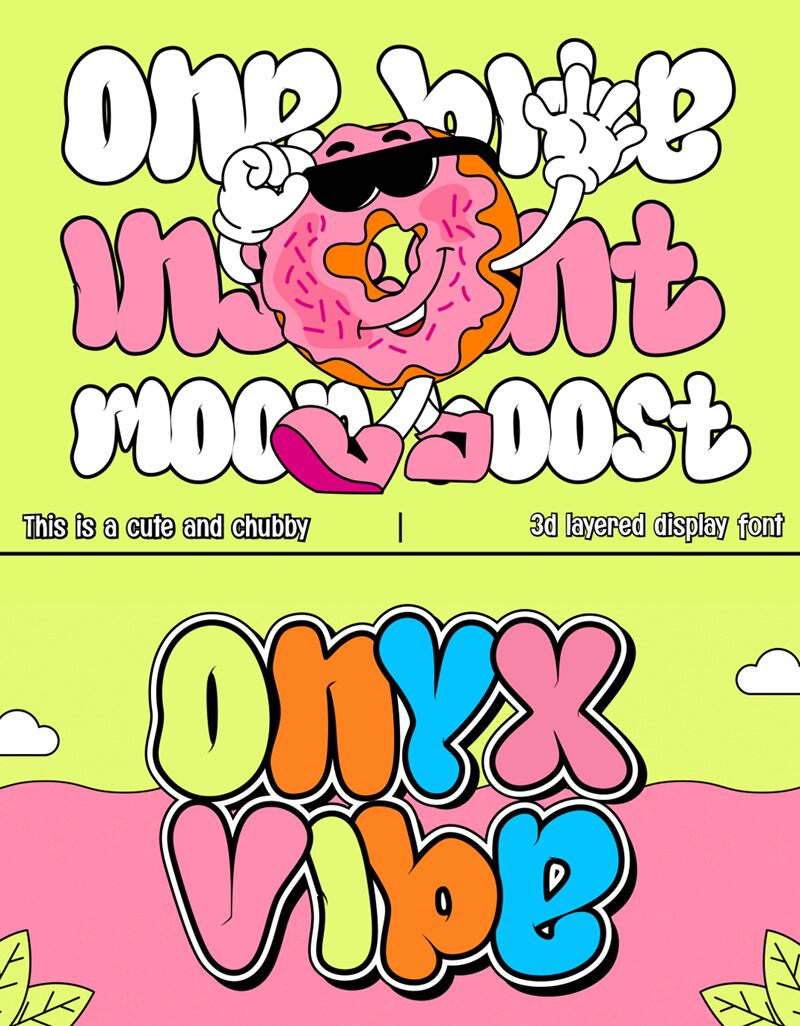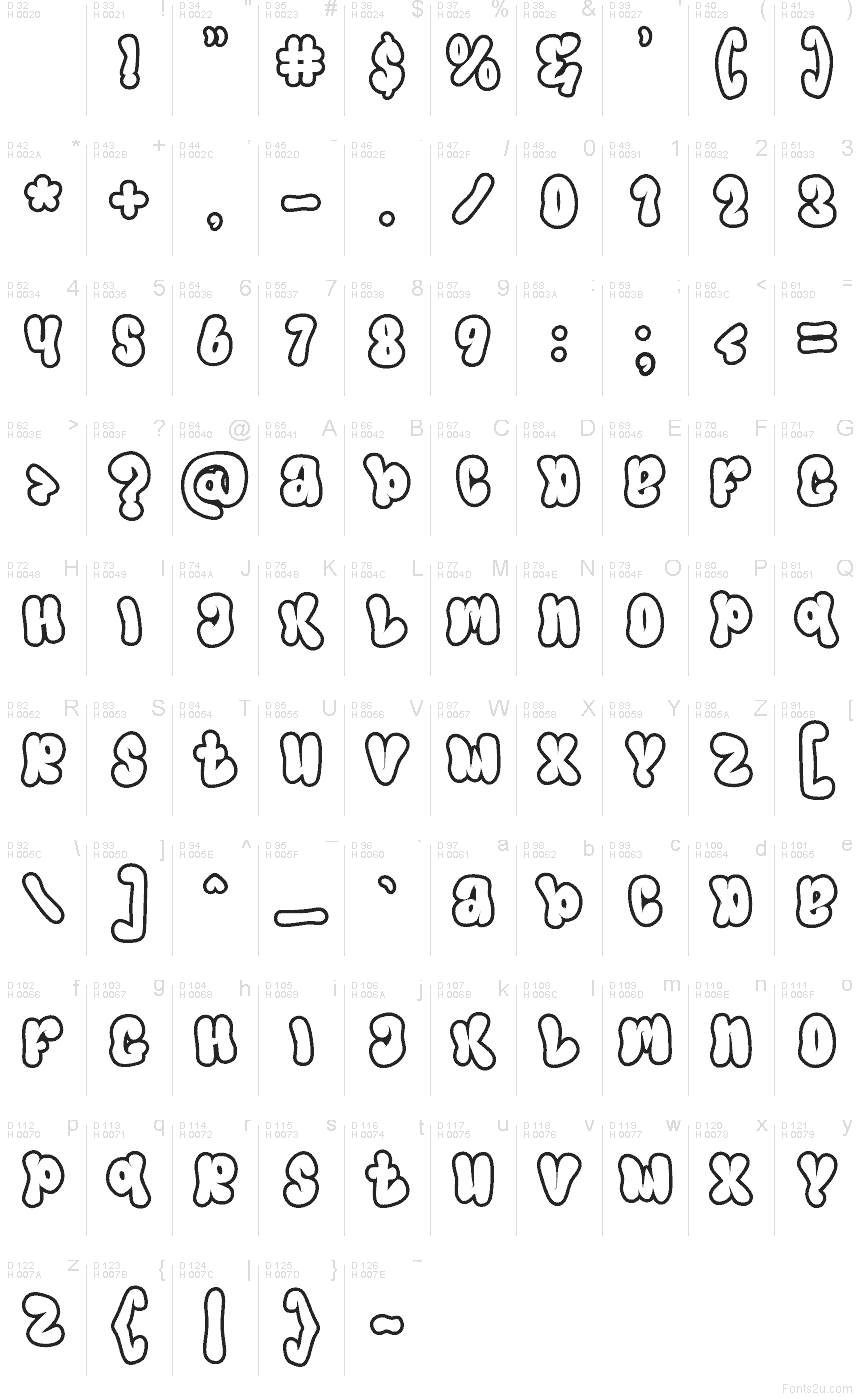
Il font Onyx Vibe Outline di Muhammad Panji Ramdhani di Figuree Studio porta in vita la famiglia Onyx Vibe con profili gonfi e rimbalzanti, che richiamano l'effetto dell'aerografo e del lettering a mano. Si tratta di un font graffiti gratuito; le sue forme ariose mantengono le parole incisive e leggibili anche quando sovrapponi le linee o le pieghi per creare un tag.
Con Onyx Vibe Outline, darai subito un tocco di carattere a sticker, loghi streetwear, poster da skate, copertine di album, miniature YouTube, volantini per eventi e banner social. Usalo in dimensioni grandi per lasciar respirare il contorno, poi abbinalo a una sans-serif condensata e nitida per didascalie e date: questo font gratuito ama gli accostamenti essenziali.